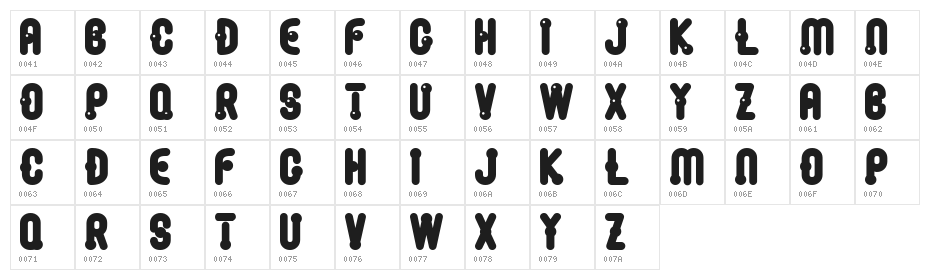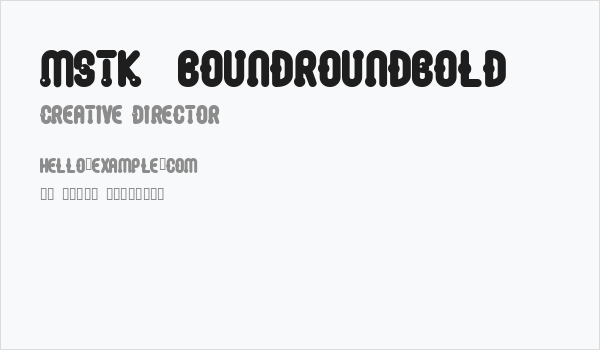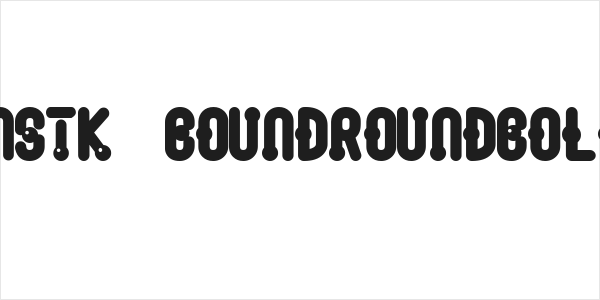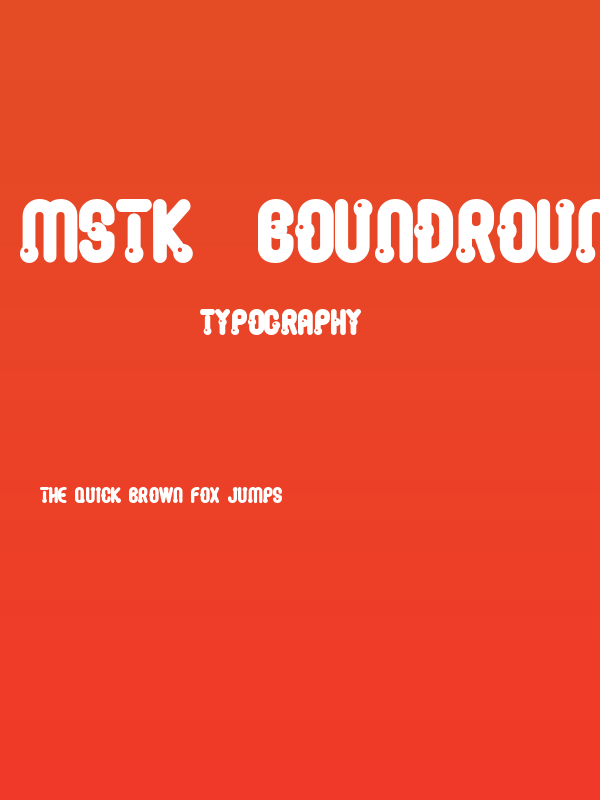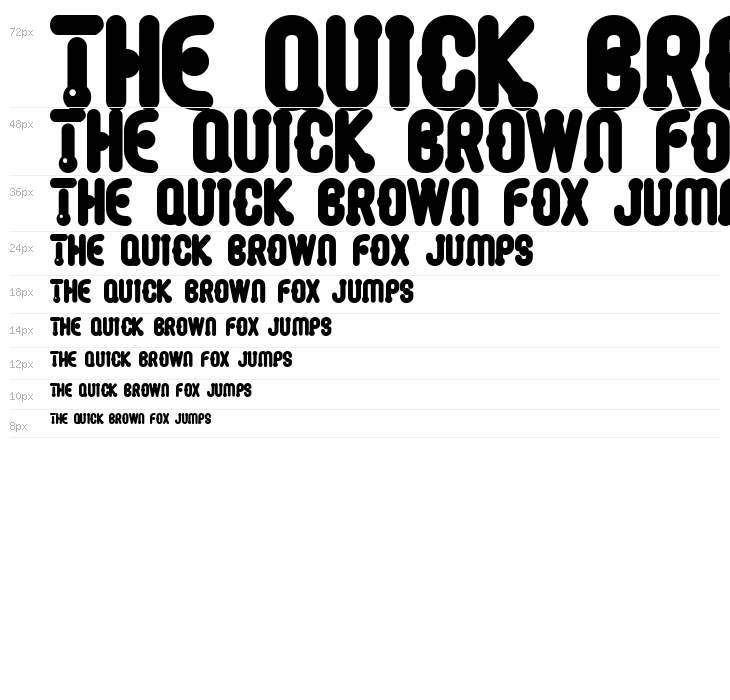
MSTK boundroundBold Font
| Vorgeschlagene Projekte | Perfect for branding, posters, headlines, and any project requiring a bold and modern aesthetic. |